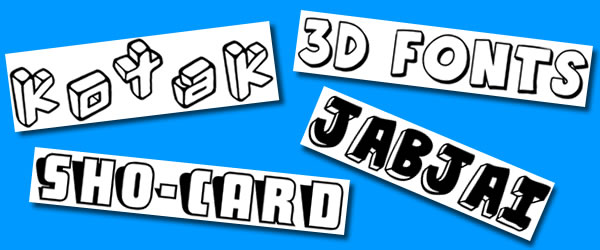
40 tipografías con efecto 3D
Hoy en día, las tipografías con efecto 3D están haciendo su camino en algunos de los diseños. Con la ayuda de estos tipos de letras, podemos hacer que los diseños de texto sean diferente de lo habitual. Cuando se utiliza con un atractivo diseño y con creatividad, el texto o palabras pueden parecer más vivos, divertidos y atractivos a los ojos de la audiencia. En el artículo A Collection of 40 Useful 3D Effect Fonts, de NaldzGraphics, podemos encontrar un escaparate de 40 tipografías útiles con efecto 3D. La colección se compone de diferentes tipos de letras en 3D para que podamos elegir lo que más nos guste. Todas estas tipografías son gratuitas.